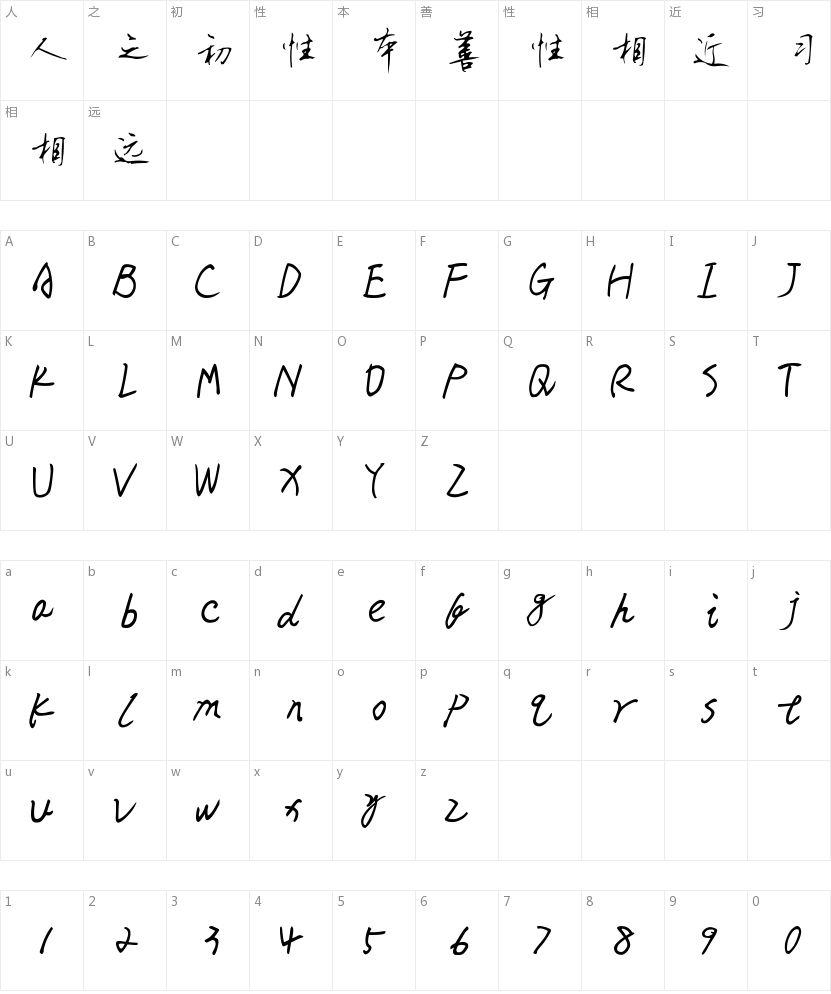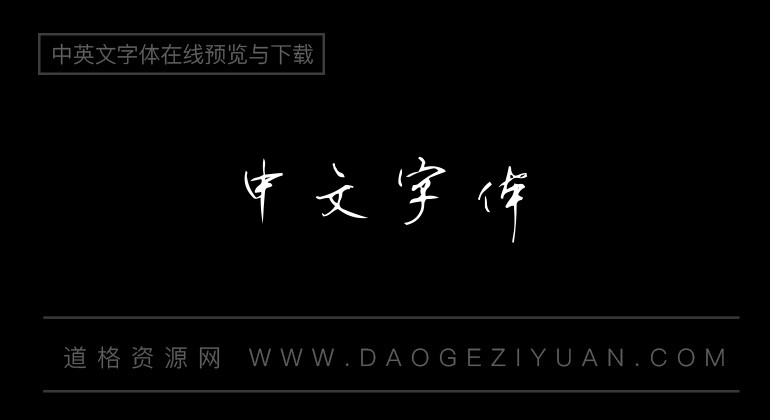
博洋行书7000
博洋行书7000是由博洋字体公司研发的一款中文字体,它采用精致的线条和细节,完美地演绎出博洋行书7000的精致风格,为用户提供了更多的选择。博洋行书7000拥有超过7000个字符,支持中文、英文和多种语言,可以满足不同领域的需求。该字体具有精致的线条,可以提供精细的排版效果,从而使文字更加清晰,简洁大方。此外,该字体还具有良好的可读性,使文字更加清晰,易于阅读。
博洋行书7000是一款非常不错的手写艺术字体,具有很好的视觉感,适合于文化类的宣传设计、商业类品牌的广告和产品包装设计以及个性化文字排版等较多场景。
博洋行书7000字符映射图